Schrift 5.–17. Jahrhundert
Über mehr als ein Jahrtausend verändert sich, wie in Mitteleuropa geschrieben wird: aus römischer Kapitalis werden Unzialen, Karolinger Minuskel, gotische Texturen — und schließlich die Mischformen der frühen Neuzeit.
Schrift ist im Mittelalter ein Handwerk wie Zimmern oder Schmieden. Mönche kopieren in den klösterlichen Skriptorien Bibeln, Chroniken und antike Autoren. Im Hochmittelalter verdichtet sich die Schrift zur gotischen Textura — eng gesetzt, kantig, ehrwürdig.
Mit Buchdruck und Renaissance treten Antiqua und Fraktur in einen jahrhundertelangen Wettstreit. Die einen wollen die klare Linie der römischen Antike, die anderen die schwarze Kraft der mittelalterlichen Tradition. Beides existiert nebeneinander, bis weit ins 17. Jahrhundert hinein.
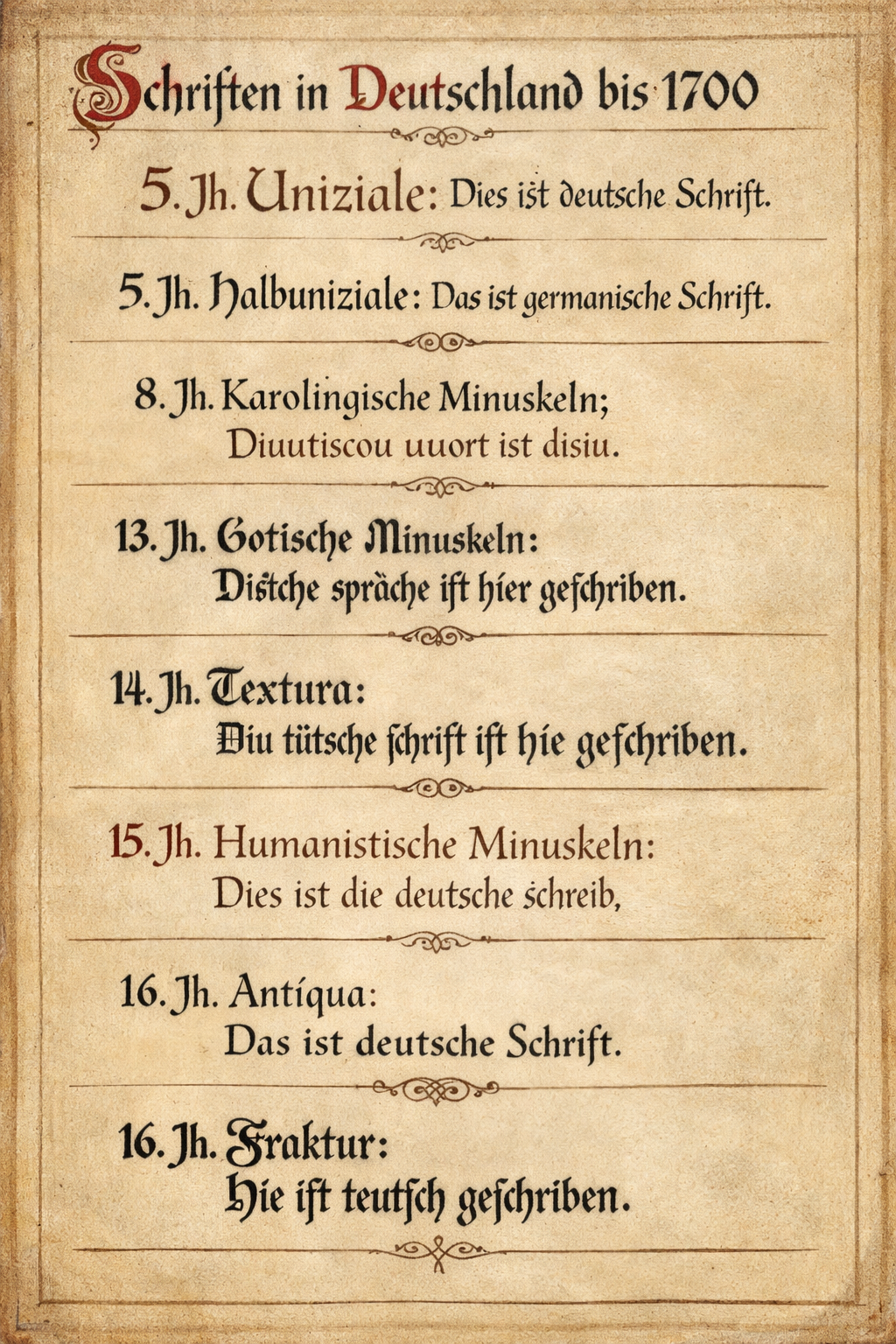
5.–17. Jahrhundert
Zwölf Jahrhunderte deutsche Schrift
Übersicht deutscher Schriftformen vom 5. bis 17. Jahrhundert
Schrift-Tafel
Vom Unzial bis zur Fraktur
Eine Tafel, viele Hände: Wer die Reihen von oben nach unten liest, sieht, wie sich Buchstaben über die Jahrhunderte verformen — runde Unzialen werden zu klaren karolingischen Minuskeln, diese verdichten sich zur Gotik und werden im Druck zur Fraktur.